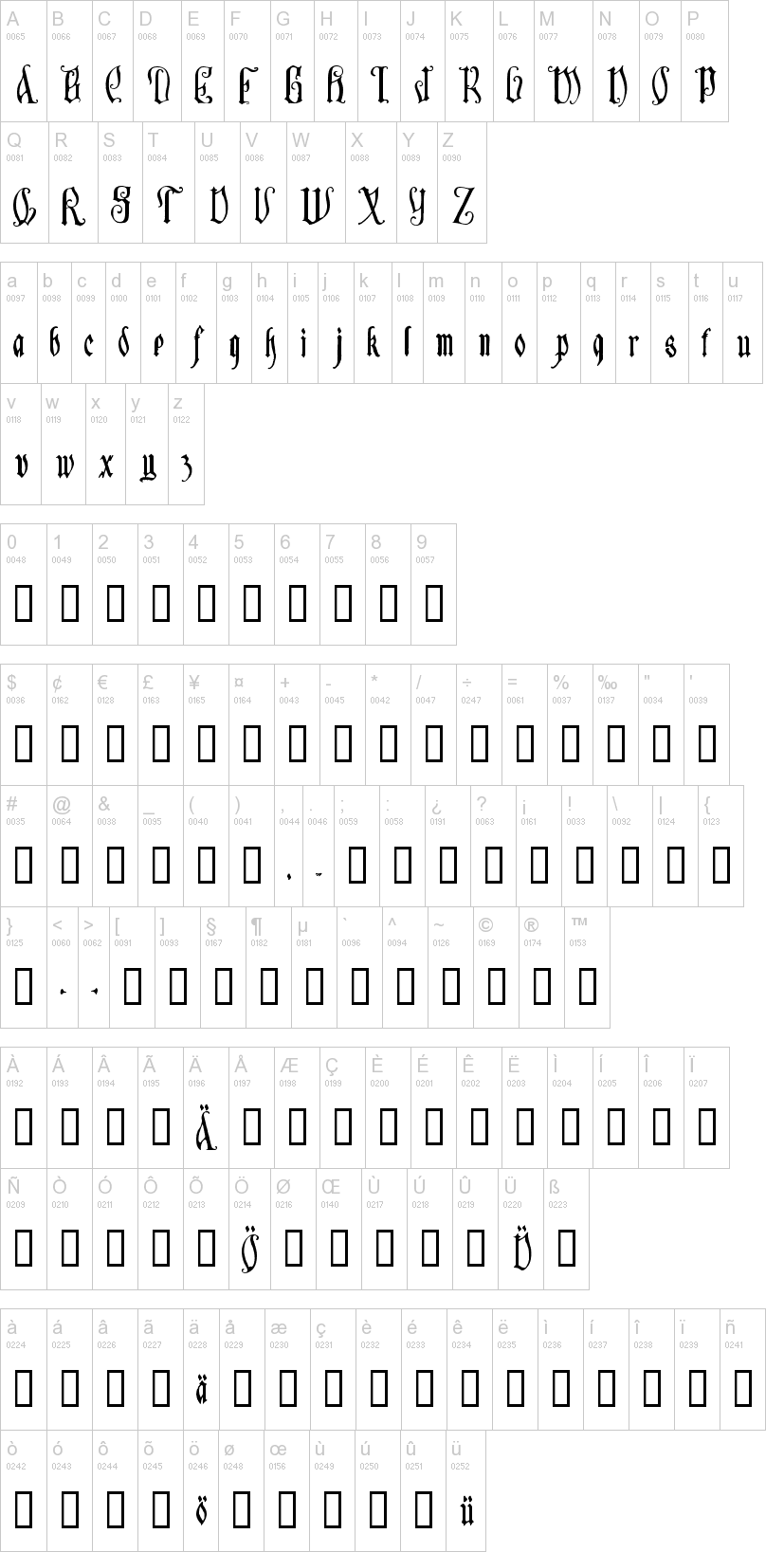
Sauerkraut是一款由英国设计师Rob Mientjes设计的字体,它具有现代感和粗犷的外观,适合在海报,标志,照片和印刷品上使用。Sauerkraut字体具有细节丰富的曲线,使其看起来更加动态,而且它的设计风格也更加简洁,可以满足大多数设计师的需求。Sauerkraut字体也可以用于网页设计,因为它具有良好的可读性,可以让网页内容更加清晰明了。内容介绍
Sauerkraut是一款非常不错的手写艺术字体,具有很好的视觉感,适合于文化类的宣传设计、商业类品牌的广告和产品包装设计以及个性化文字排版等较多场景。